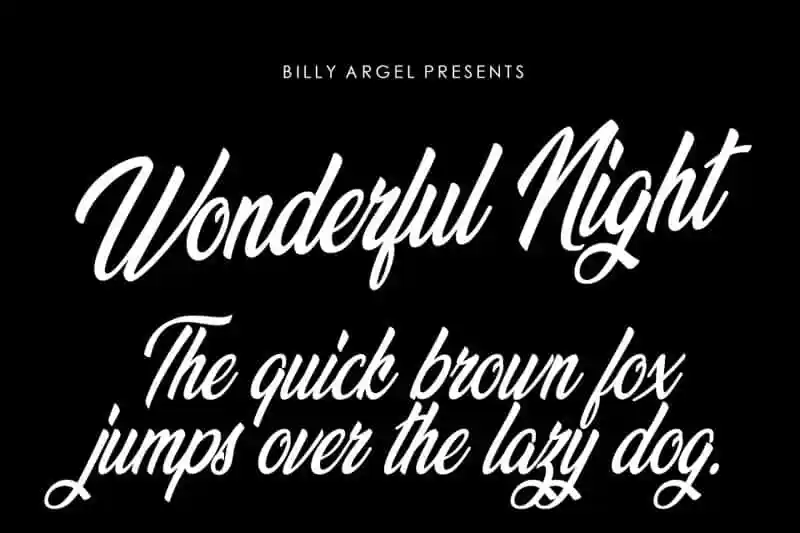
Wonderful Night Script Font – Download Grátis
A Fonte ‘Wonderful Night Script’ é uma excelente escolha para qualquer designer que busca agregar sofisticação ao seu trabalho. Desenvolvida pelo designer Hamilton, essa fonte é notável pela sua personalidade única e delicadeza elegante, proporcionando um apelo sólido e profissional aos projetos. ‘Wonderful Night Script’ é mais do que uma simples adição à paleta de suas ferramentas: ela se adapta a uma ampla variedade de designs, permitindo-lhe alcançar um nível superior em praticamente qualquer projeto. Com uma escrita fluida e relaxada, essa fonte está sempre pronta para transformar seus trabalhos nas melhores obras possíveis. É perfeita para projetos que exijam graciosidade e classe ao mesmo tempo em que oferecem flexibilidade suficiente para atender a diversas necessidades de design. Seja você um designer gráfico, um designer web ou qualquer outra área do design, essa fonte é uma opção ideal para quem busca personalizar seus trabalhos com graça e elegância. Composta pelo designer Hamilton, ‘Wonderful Night Script’ é mais do que uma ferramenta para fazer design; ela transforma os ideais criativos em realidade visível. Se você está pronto para criar algo extraordinário, adicionando esta fonte às suas habilidades poderia significar o começo de um novo nível de expressão visual e criativa. Experimente essa fonte na próxima vez que estiver desenhando ou editando seu próximo design e veja como ela irá revolucionar seus trabalhos.